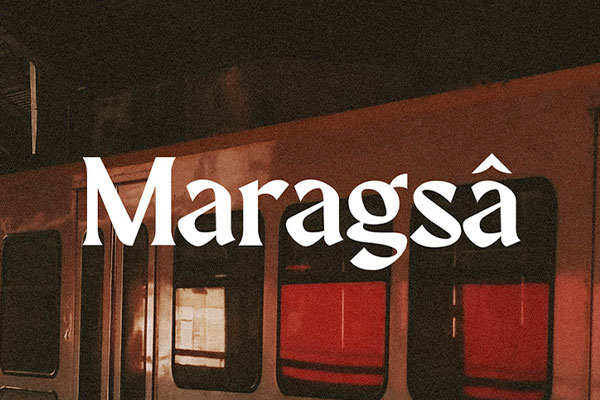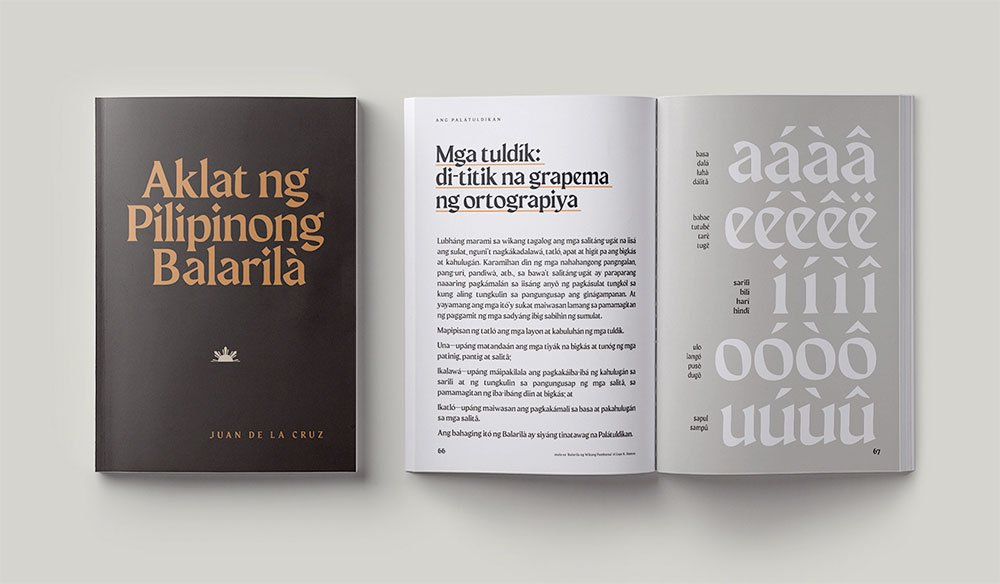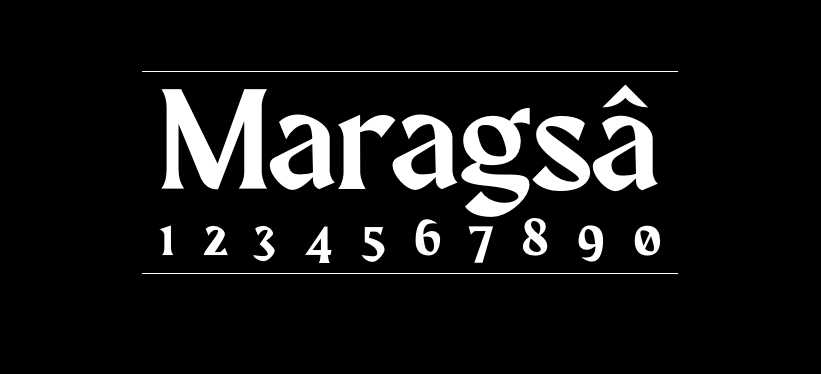
Maragsâ
Maragsâ字体介绍
Maragsâ的作者是来自菲律宾的John David Maza,Maragsâ是一种半斜体显示字体,其形状归因于一种重音符号,该重音符号被用作引导菲律宾单词正确发音的重音符号-pakupy重音,其锥形尖端预示了锐利的边缘,匆忙的笔触和突然的声音削减字符,类似于应讲重音的方式。
术语“maragsâ”指的是在菲律宾的语言发音的话当有压力同时出现的方式(diin)和喉塞音(impit)在最后一个音节。它通过在单词的最后元音上附加一个抑扬符或 “pakupyâ”标记来表示。
在菲律宾的日常生活中,很少出现带有变音符号的文字,因此理解某些菲律宾语单词在很大程度上取决于上下文。但是,请记住,简单添加重音符号可以完全改变单词的含义。
术语“maragsâ”指的是在菲律宾的语言发音的话当有压力同时出现的方式(diin)和喉塞音(impit)在最后一个音节。它通过在单词的最后元音上附加一个抑扬符或 “pakupyâ”标记来表示。
在菲律宾的日常生活中,很少出现带有变音符号的文字,因此理解某些菲律宾语单词在很大程度上取决于上下文。但是,请记住,简单添加重音符号可以完全改变单词的含义。
Maragsâ字体应用示例